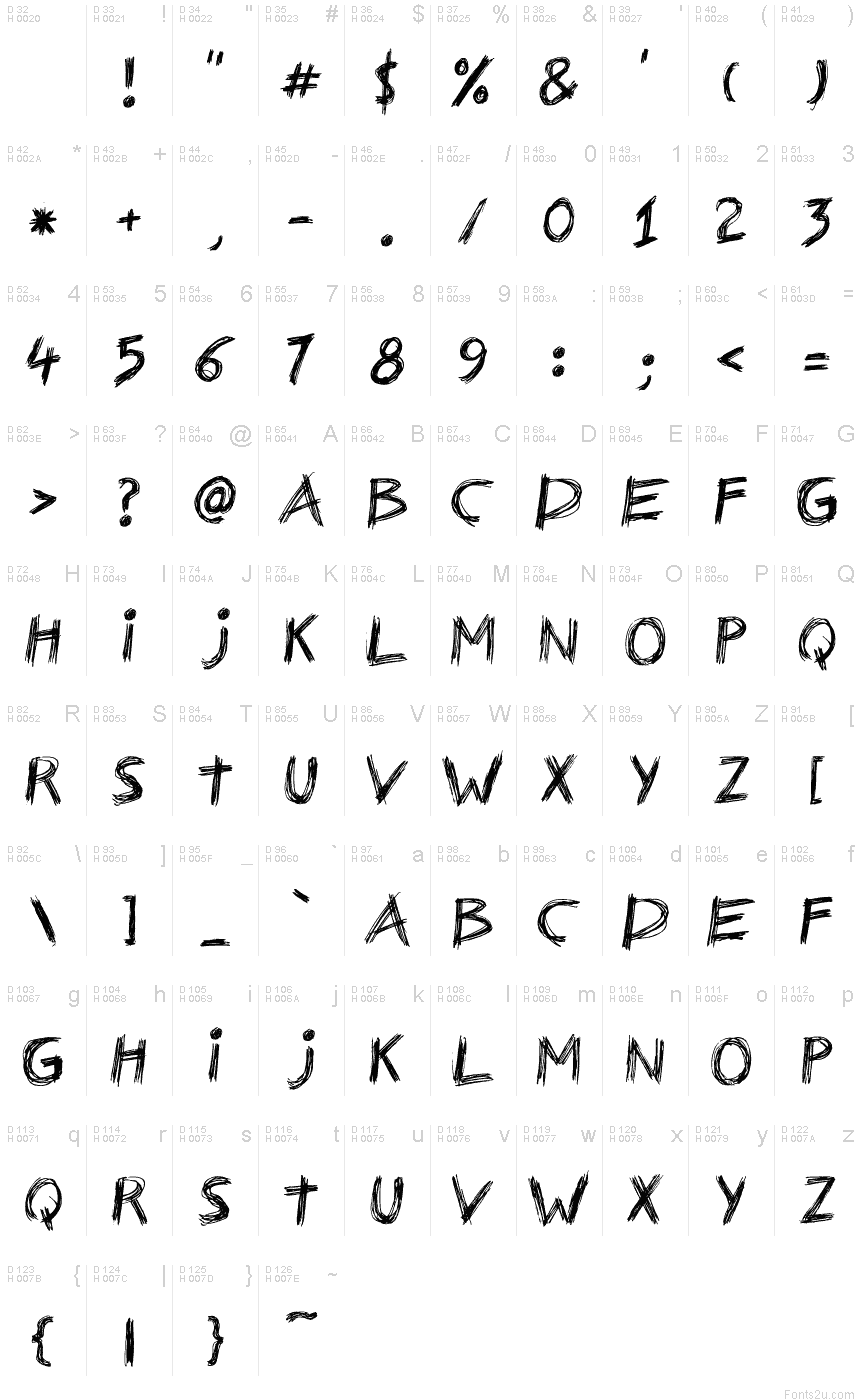
Nerwus od flashFONT 2000 je bezplatný font typu trash display se škrábanou texturou a roztřepenými tahy, díky kterým každé písmeno působí ošoupaně. Zubaté okraje a opakující se přerušení, jako kdyby písmo tvořil neustále odskakující hrot pera, dodávají slovům neklidný, spěšný rytmus, aniž by však ztratila svůj základní tvar.
Nerwus se hodí na plakáty ke koncertům, hororové titulky, ziny, grafiku na nálepky, herní design nebo drsné logo značky, kde toto vyškrábané zpracování nese atmosféru i bez dalších ozdob. Vnáší do textů na plakátech, varovných štítků a undergroundové grafiky syrový, improvizovaný nádech, který působí, jako by byl nakreslen narychlo a záměrně nedokončený.
Nerwus